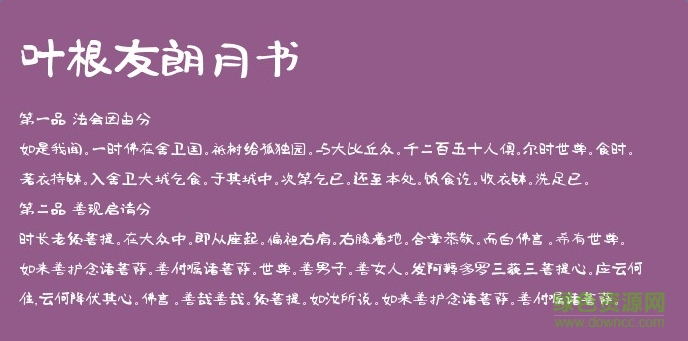
葉根友朗月書體
葉根友朗月書字體是一款休閑文雅風(fēng)格字體軟件,朗月書體筆畫以手寫為主,創(chuàng)意十足,十分俏皮,非常受年輕人的熱愛與追捧,還有更多好看字體歡迎來(lái)綠色資源網(wǎng)下載體驗(yàn)!
葉根友朗月書字體根據(jù)葉根友手寫體制作,該字體自然灑脫,看起來(lái)左暈右倒但是卻不是凌亂,而是一種過(guò)渡的唯美!
該字體筆畫隨意自然,看似灑脫放蕩不羈,卻不失工整,非常有韻味,在印刷廣告字體設(shè)計(jì)方面有著不錯(cuò)的應(yīng)用,創(chuàng)意十足,值得收藏使用!